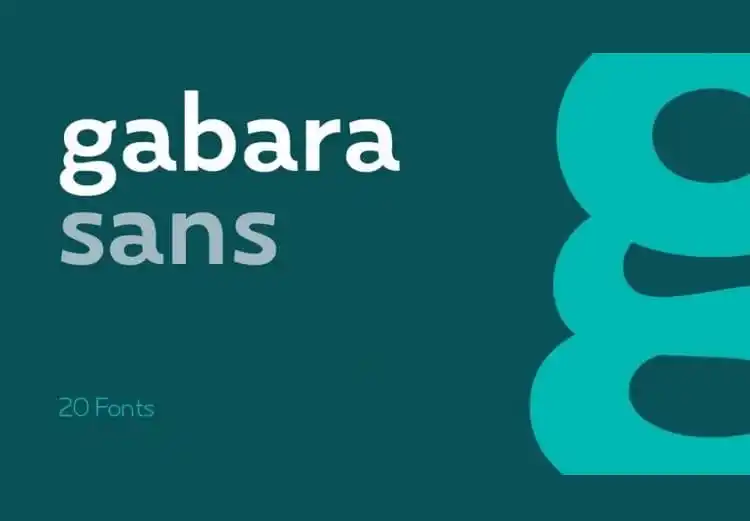
Gabara Sans Serif Font – Download Grátis
A Gabara Sans Serif Font é uma família de fontes serifadas que traz ao seu projeto uma sensação de leveza e diversão, mas com um toque mais forte e alegre. Desenvolvida pelo designer Serdar Öztürk na 99designs, essa fonte combina facilidade de uso para texto longo ou curto, garantindo um bom equilíbrio entre leitura confortável e design vibrante. Além disso, a fonte oferece suporte multilingue e ligaturas personalizadas, tornando-a uma escolha versátil que atende às necessidades de projetos variados. Seja para uso em parágrafos ou cabeçalhos, a Gabara Sans Serif Font é uma opção ideal para quem busca um estilo moderno e divertido sem comprometer a legibilidade e facilidade de uso da sua escrita.